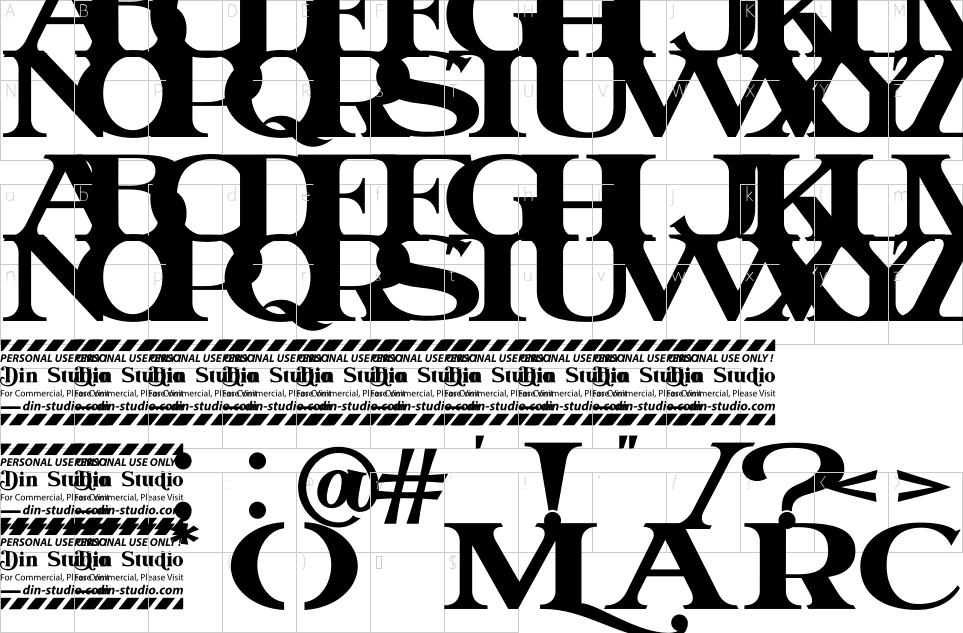
A fonte Marcelo é um conjunto de letras levemente romântico e elegante, ideal para criar designs para o ambiente moderno. Desenvolvida pela Din Studio, Marcelo é uma fonte grata que tem conquistado um grande número de usuários, sendo baixada mais de 3.728 vezes. Suas linhas suaves e harmoniosas acentuam qualquer texto, tornando-a perfeita para criações de blog, gráficos de redes sociais e design gráfico em geral. Além disso, sua versão para Windows e Mac oferece praticidade para profissionais de design que buscam uma fonte de qualidade sem precisar fazer investimentos.